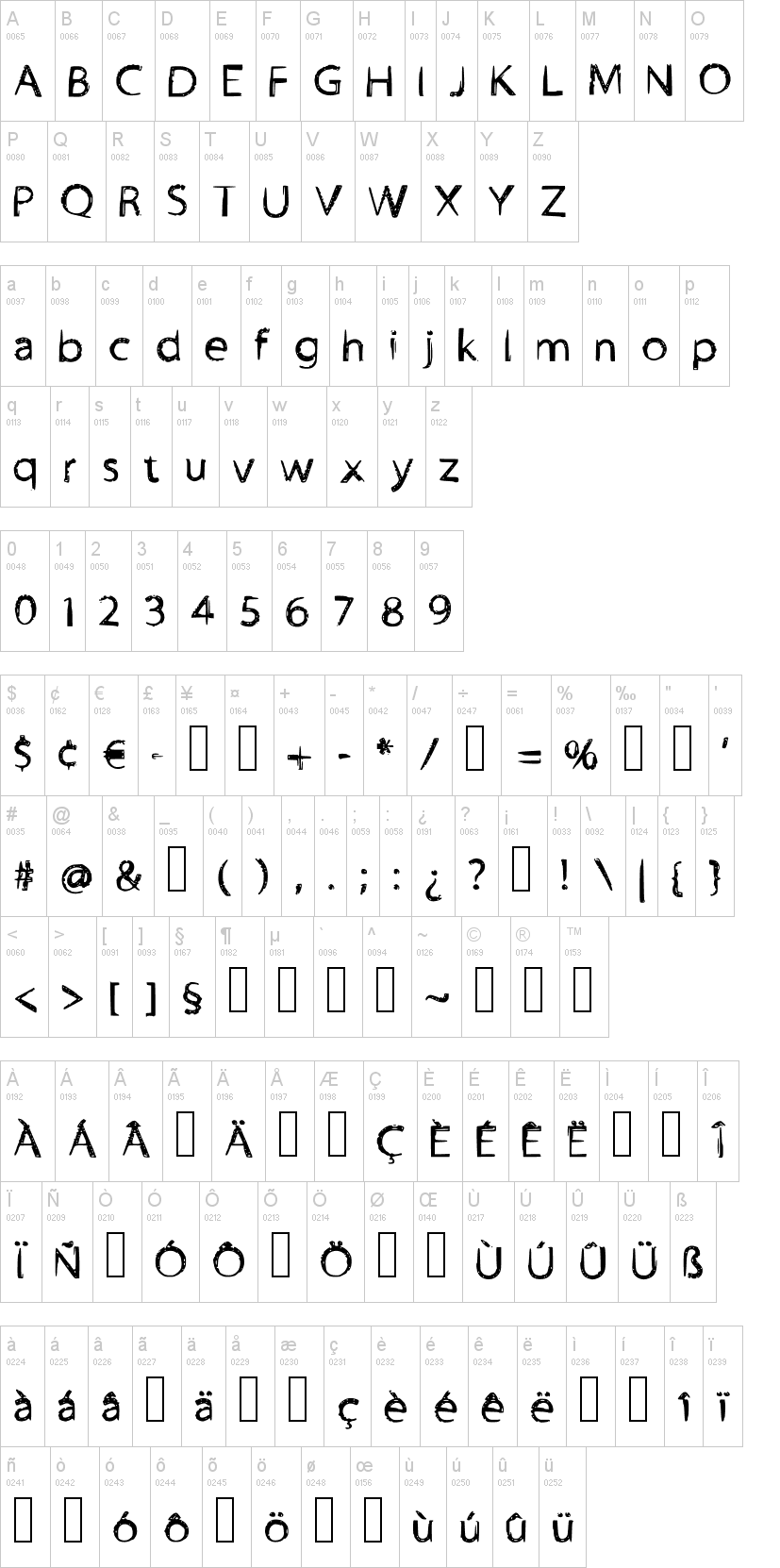
Boro 字体是一种手写风格的无衬线字体,设计师为其注入了手写的温暖和个性。它的字形不规则,有些字母的笔画是断断续续的,给人一种自然、随性的感觉。Boro 字体适合用于海报、广告、设计等领域,可以为设计作品增添一份生动、独特的气息。此外,Boro 字体还提供了多种字重和样式,可以满足不同需求的设计师和用户。内容介绍
Boro是一款非常不错的手写艺术字体,具有很好的视觉感,适合于文化类的宣传设计、商业类品牌的广告和产品包装设计以及个性化文字排版等较多场景。